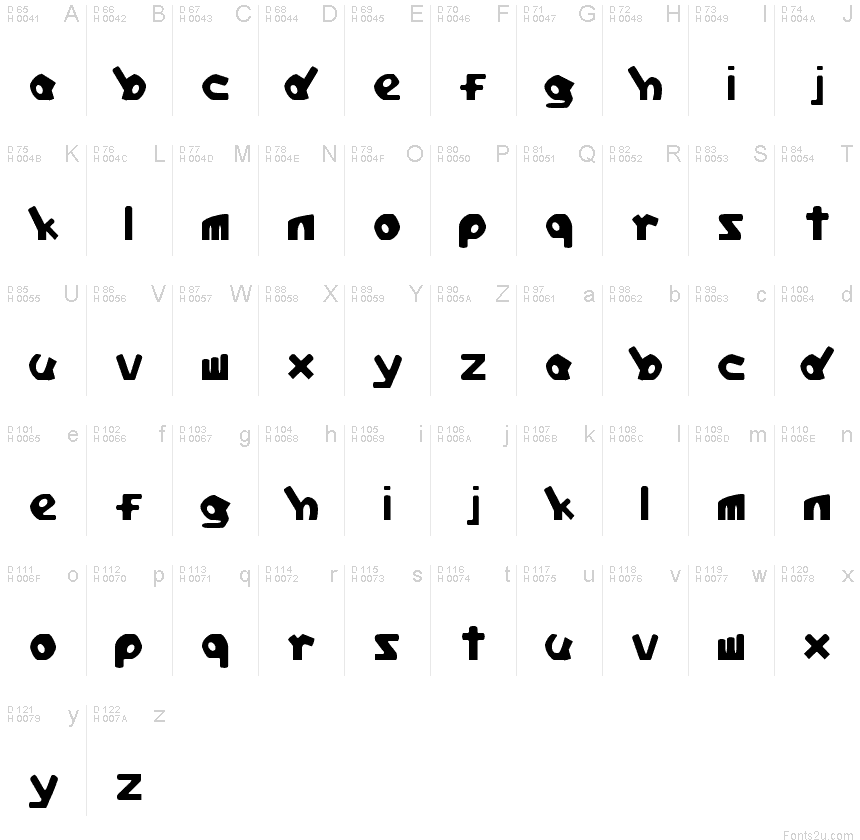
Sanctuary è un font display gratuito e distorto, con una silhouette massiccia che ricorda i collage di carta e un'atmosfera retro vagamente inquietante. Le lettere sembrano intagliate da forme nere e morbide, con angoli arrotondati, spigoli improvvisi e un ritmo irregolare che rende il carattere giocoso anziché caotico.
Questo conferisce a Sanctuary un posto naturale nei titoli dei poster, sulle copertine degli album, nelle testate delle fanzine, nel branding dei bar e nei titoli video, dove una leggera irregolarità aiuta a trasmettere un effetto artigianale. Essendo un font gratuito, è perfetto anche per nomi brevi sulle confezioni, grafiche per eventi e veloci header per i social, specialmente se cerchi lettere bold e compatte che risultino stravaganti, amichevoli e un po' fuori dagli schemi.
Sanctuary